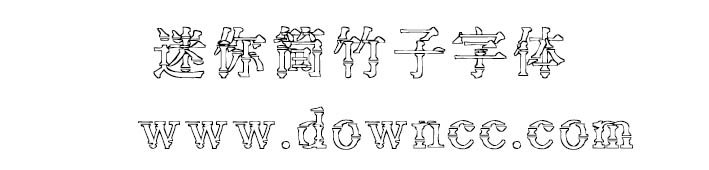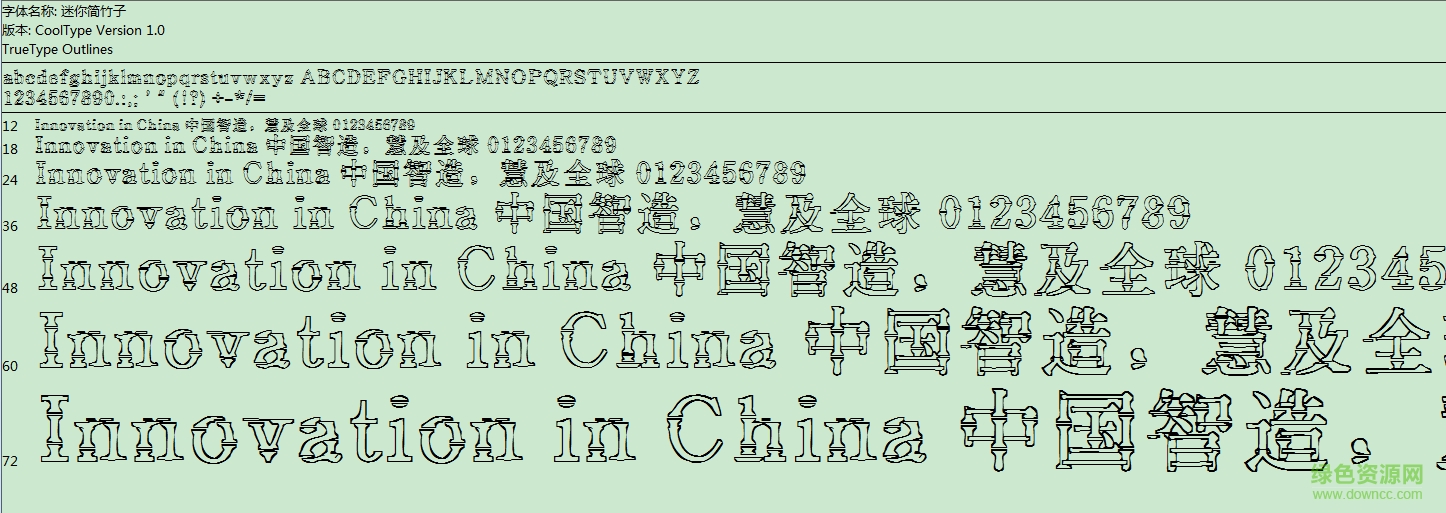
迷你簡(jiǎn)竹子字體是一款非常有特色的迷你字體,這款字體和竹子非常的相似,字形靈秀清麗,看上去非常的漂亮美觀,有需要的朋友可以來綠色資源網(wǎng)下載喲!
迷你簡(jiǎn)竹子是一款用于美工設(shè)計(jì)方面的字體,該字體樸茂工穩(wěn)、靈秀清麗、結(jié)體嚴(yán)整并有竹子效果,看上去十分美觀,非常統(tǒng)一,且字庫完整,可以廣泛應(yīng)用于廣告設(shè)計(jì)、宣傳海報(bào)、ppt、影視制作以及內(nèi)容用字等領(lǐng)域,有需要的朋友可以免費(fèi)下載收藏。